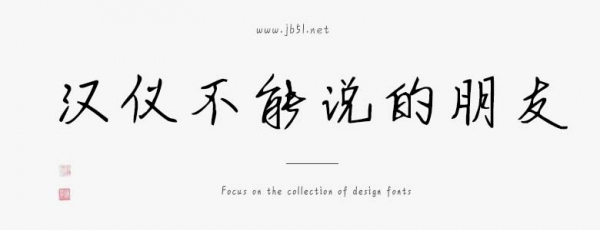
漢儀不能說(shuō)的朋友簡(jiǎn)是由漢儀字庫(kù)出品,字體筆觸纖細(xì),書(shū)寫流暢灑脫,適合應(yīng)用于藝術(shù)設(shè)計(jì)、平面宣傳設(shè)計(jì)、網(wǎng)頁(yè)設(shè)計(jì),書(shū)法字帖等領(lǐng)域,需要的朋友可以前來(lái)本站下載。